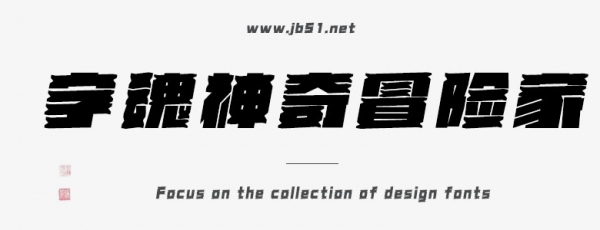
字魂神奇冒險(xiǎn)家是由字魂字庫推出的藝術(shù)字體,字體筆觸粗實(shí),字體類型偏向創(chuàng)意字體,具有動(dòng)漫、可愛的風(fēng)格,具有很好的視覺感,適合應(yīng)用于藝術(shù)設(shè)計(jì)、平面宣傳設(shè)計(jì)、網(wǎng)頁設(shè)計(jì),書法字帖等領(lǐng)域。
字魂神奇冒險(xiǎn)家字體是由字魂創(chuàng)意字庫設(shè)計(jì)并生產(chǎn)的一款可商用的字體,被收錄于字魂先鋒系列。該字體支持GB-2312標(biāo)準(zhǔn),包含6942個(gè)中文、字母、符號(hào)和數(shù)字,字體類型偏向創(chuàng)意字體,具有動(dòng)漫、可愛的風(fēng)格,在市面上廣泛用于餐飲食品、游戲動(dòng)漫、運(yùn)動(dòng)戶外等場(chǎng)景。